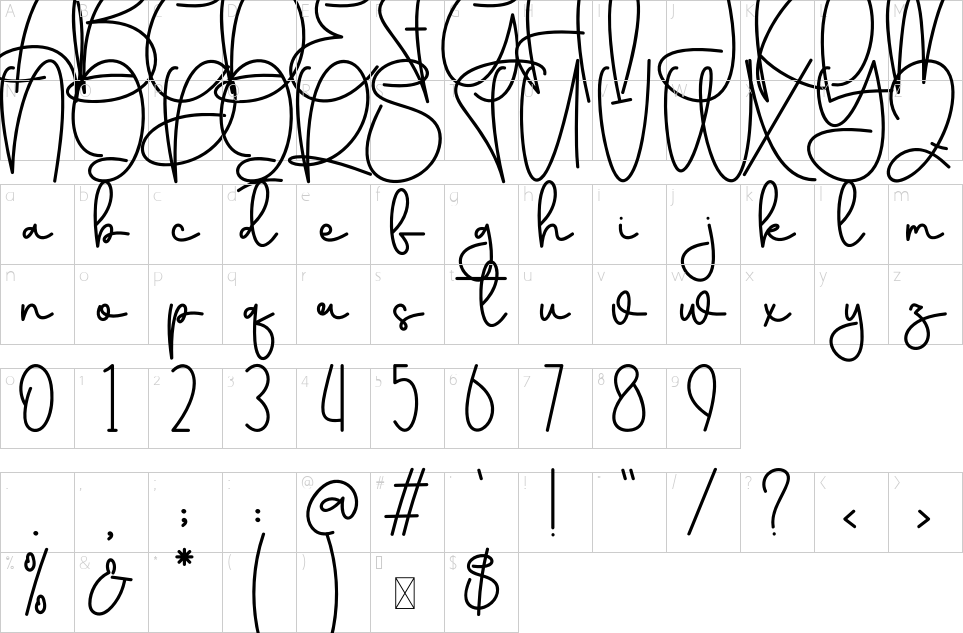
Aqui está uma descrição em português do Brasil para a página de download da fonte ‘Party Christmas Font | 1001 Free Fonts’: Descubra a festa natalina ideal com a Party Christmas Font. Desenvolvida pelo designer scratchones, essa fonte é perfeita para adicionar um toque especial às suas criações natalinas. Com esse design inovador e com um visual acolhedor, você pode personalizar rótulos de presentes, tags de presentes e até mesmo cartões de natal com uma aparição festiva e irreverente. Com sua facilidade de uso e seu estilo inconfundível, a Party Christmas Font é uma ótima opção para quem procura uma fonte natalina divertida. Baixe-a agora e transforme suas criações natalinas em verdadeiros eventos de festa.